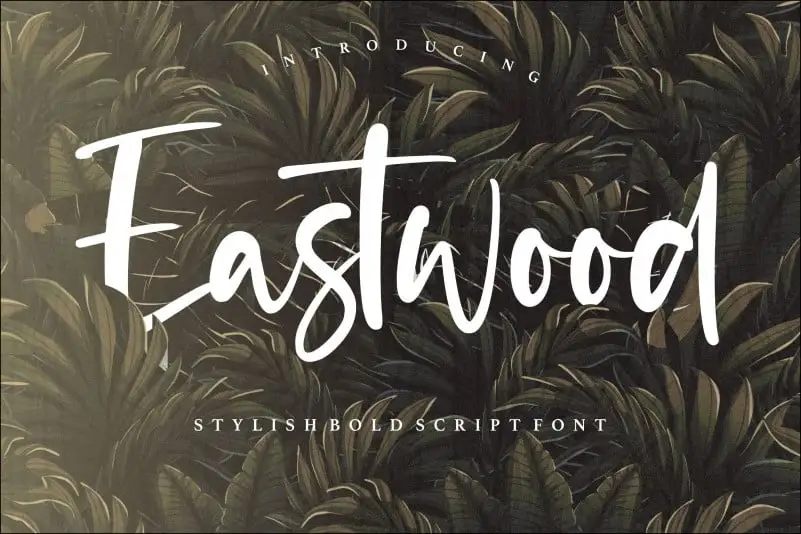
Eastwood Stylish Bold Script Font – Download Grátis
A fonte Eastwood Stylish Bold Script é perfeita para aqueles que procuram uma fonte elegante para agregar estilo às suas criações digitais. Ideal para arquivos de embalagem, identidade visual e projetos de revistas, ela também pode ser usada em mídias sociais, casamentos ou qualquer outro contexto onde você deseja destacar os textos acima de fundo. Seu design suave e sofisticado faz dele um recurso indispensável para todos os criadores de conteúdo que buscam incorporar uma personalidade única em seus trabalhos. Com a Eastwood Stylish Bold Script, suas ideias podem realmente brilhar sobre o plano de fundo.